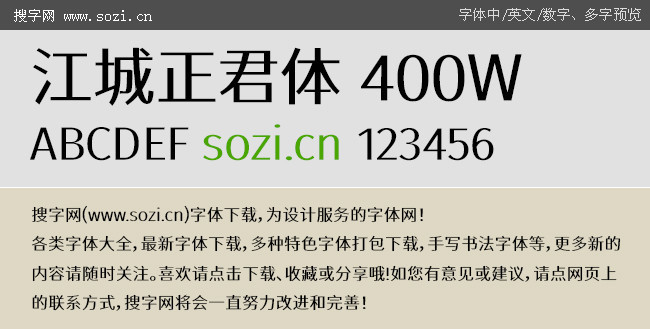
江城正君體 400W
搜字網(wǎng)提供一款江城正君體 400W中文藝術(shù)字體下載,江城月湖體是基于思源系列字體改造而成,所以擁有思源字體的超大字符集血統(tǒng),簡體和繁體都基本上不缺字。這款字體字形靈秀清美,橫粗豎細(xì)的風(fēng)格頗為特別,圓潤的筆畫中又帶著一點(diǎn)動感,比較適合用作正文,標(biāo)題,偏柔美風(fēng)格的設(shè)計。